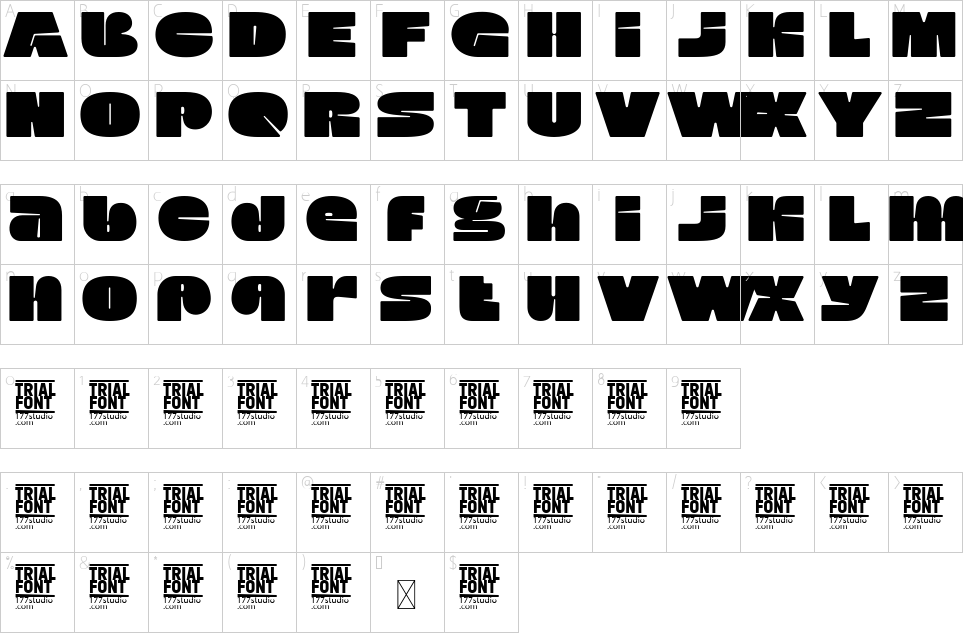
A Deepest Lighting é uma fonte de design arrojado projetada por 177studio.com, disponível para download tanto no Windows quanto na plataforma Mac. Esta fonte apresenta linhas aguçadas e esculpidas com precisão, criando um efeito quase realista em textos. Suas características incluem tons de cinza muito profundos que se destacam notavelmente nas páginas de sites ou documentos digitais. A elegância da Deepest Lighting se combina perfeitamente com texturas modernas e linhas geometricamente perfeitas, tornando-a uma escolha ideal para designers buscando um texto atraente e sofisticado. Com seu design sóbrio e forte, a fonte é perfeita para uso em sites de notícias, jornais online ou qualquer outra aplicação que requer um estilo elegante e profundo. As opções de download simples e rápida garantem que você possa incorporar esta linda fonte ao seu layout com facilidade.